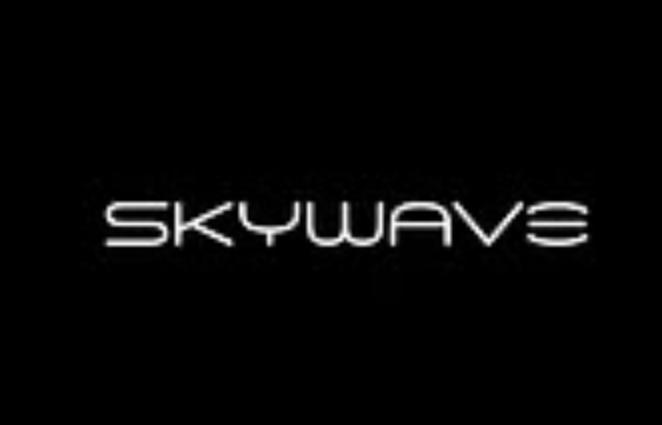
Skywave - это крутой, техно и забавный дисплейный шрифт. Независимо от темы, этот шрифт будет невероятно полезен для вашей библиотеки шрифтов, поскольку он может улучшить любое творение.